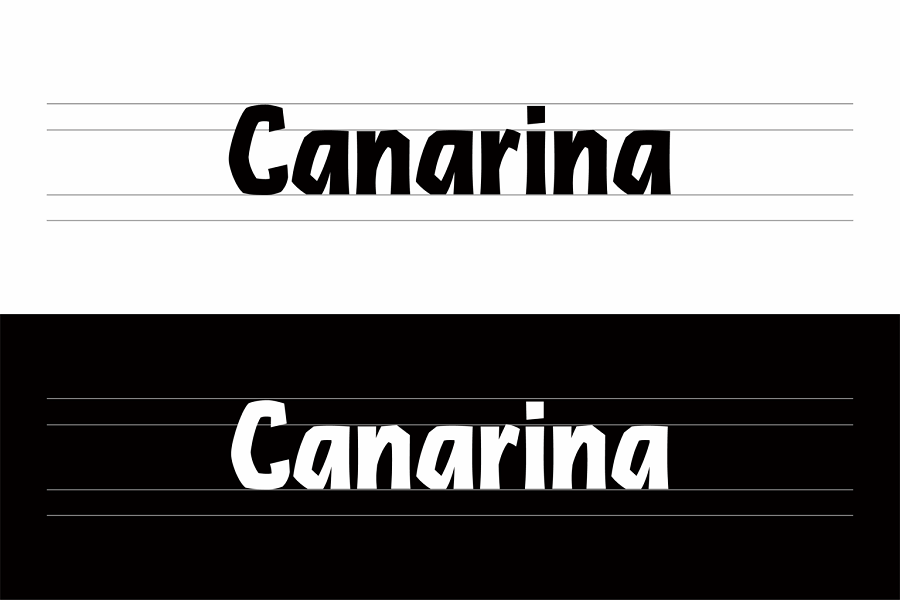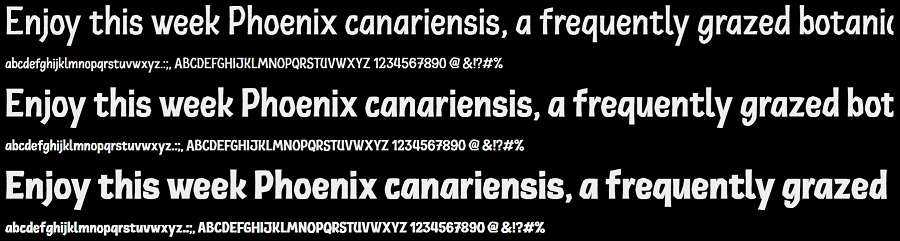
Canarina 是由法国艺术总监 Ariel Martín Pérez 以西班牙加那利群岛为灵感设计的一款免费可商用的无衬线字体。名字取自当地一种名为 Canarina canariensis 的红色钟形花朵的藤蔓植物,也是加那利群岛的象征之一。
虽然名字源自加那利群岛,但 Canarina 的设计灵感并非来自当地的印刷传统,而是借鉴了当地两位艺术家 Eduardo Millares Sall(Cho-Juaá字符创作者)和 César Manrique(抽象雕塑家)的作品。将立体造型轮廓转化为字母的宽幅折角,呈现出类似火山岩、多肉植物叶片的几何图案样式,很有地域历史特色。
Canarina 属于个性型装饰字体,而非通用型阅读字体。所以更适合各类标题/标识设计或者文创周边的创意视觉设计,而非长文本的正文排版以及正式商务场合。简单说就是文字「短、大、少」的地方用 Canarina 很合适,但用在「长、小、多」的文字上则比较拉胯。